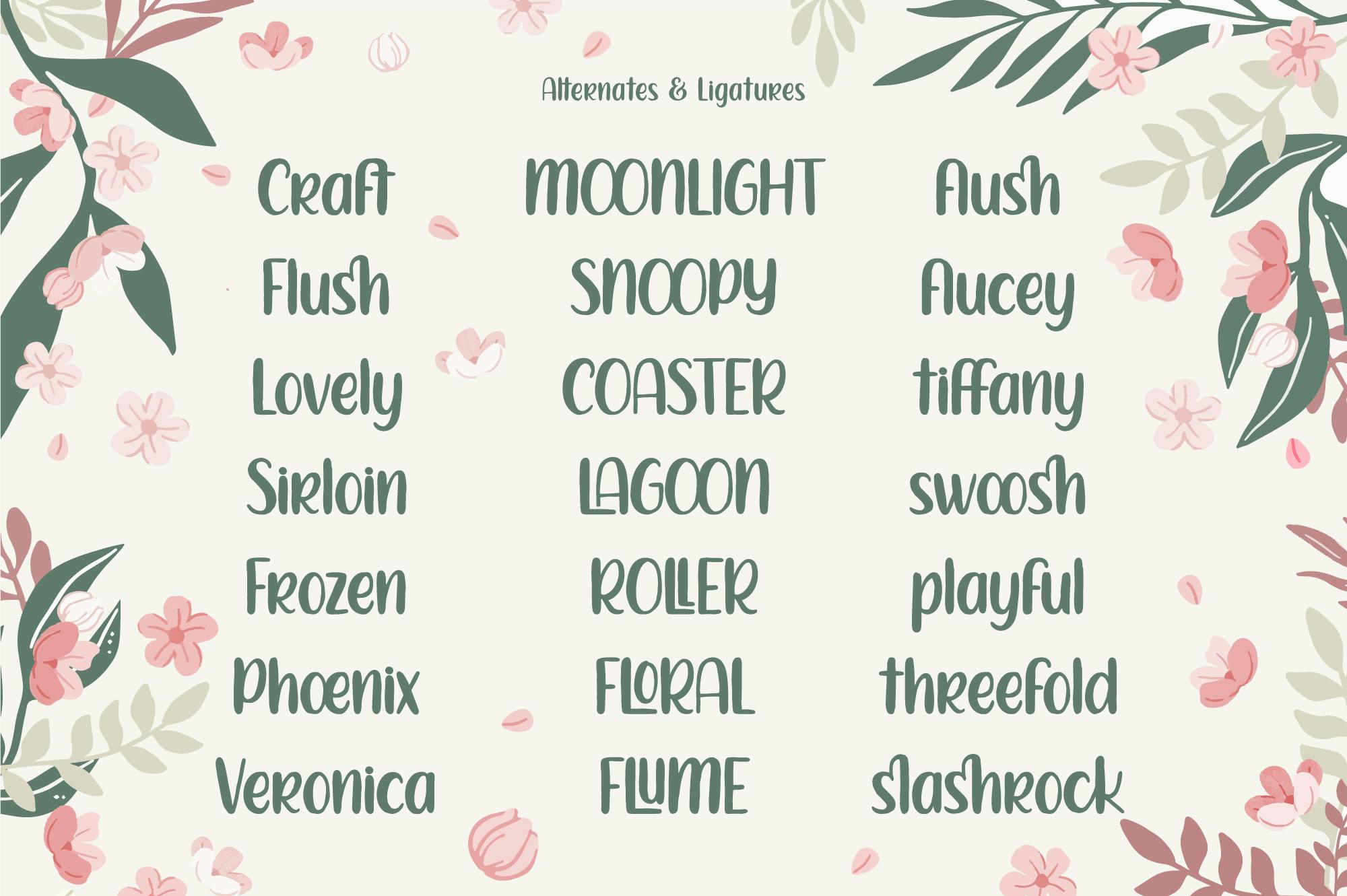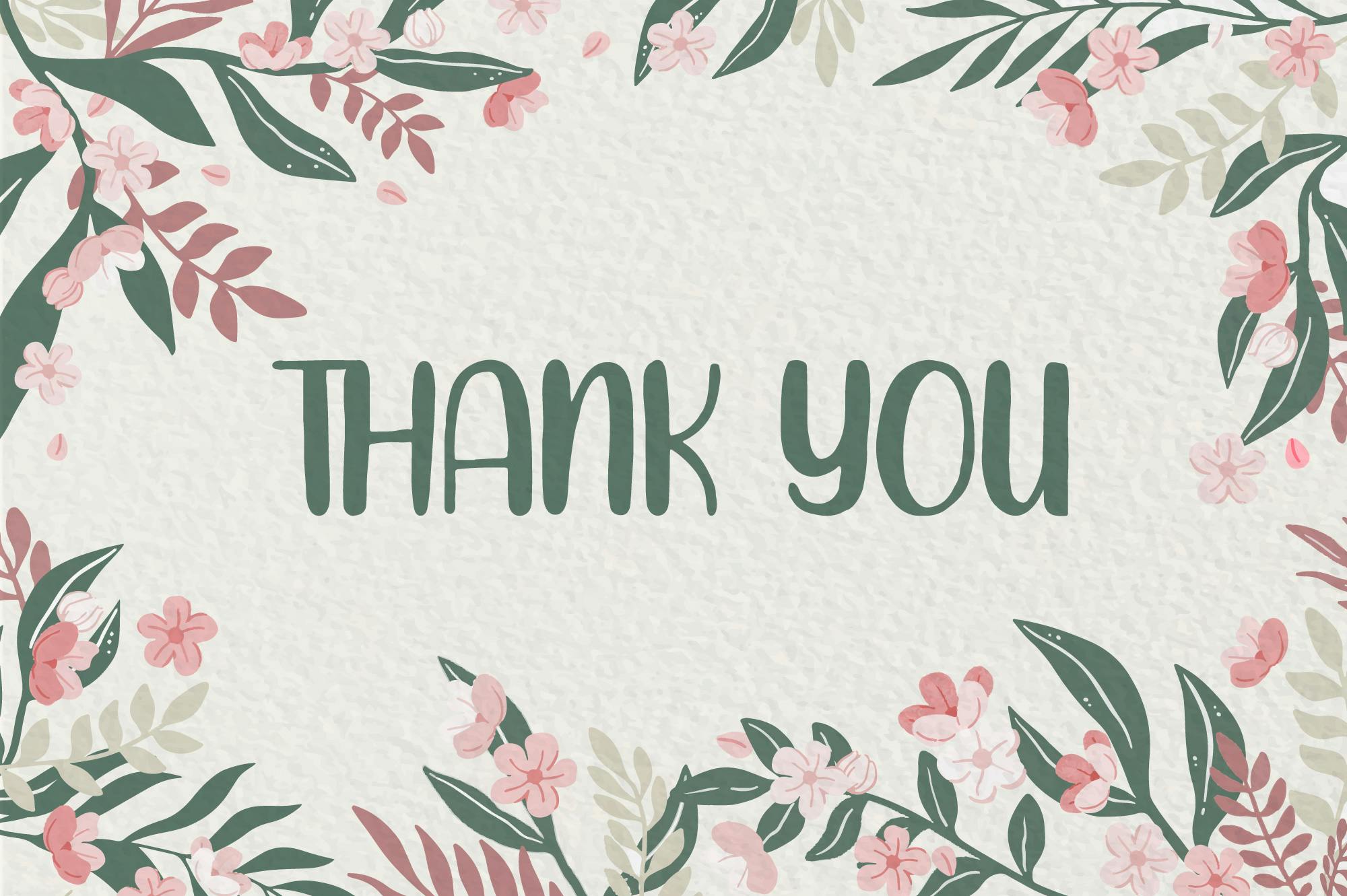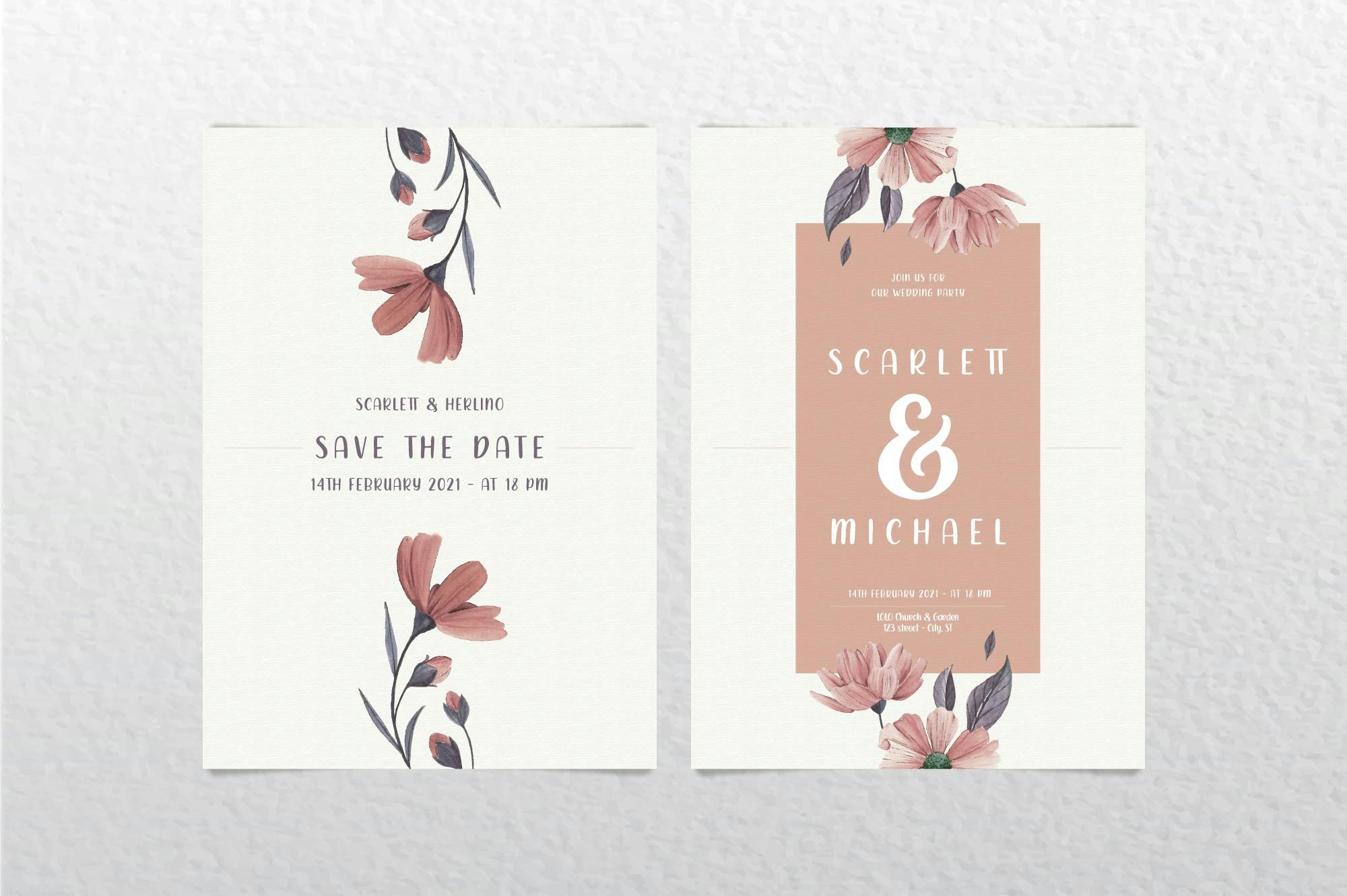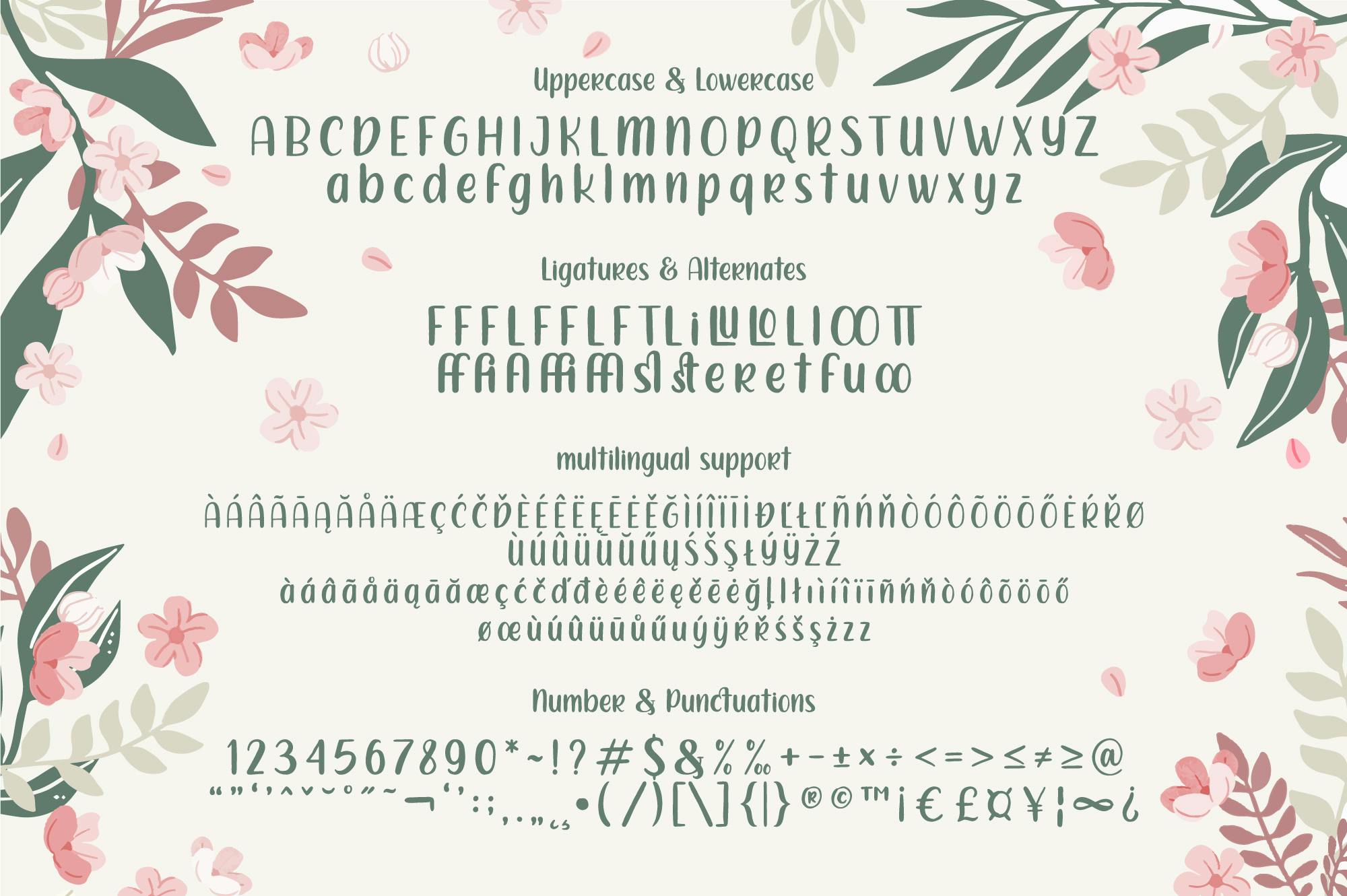
فونت Harelson Crafter با الهام از زیبایی و جذابیت، به طراحان این امکان را میدهد تا خلاقیتهای خود را به نمایش بگذارند. این فونت شامل انواع مختلف حروف از جمله حروف بزرگ، کوچک، لیگاتورهای اختیاری و لیگاتورهای جایگزین است. این فونت برای طراحیهای زیبا مانند پوسترها، محصولات، لباسها، بروشورها و کارتهای ویزیت مناسب است.